우리는 문서를 작성할 때나 계약서에 서명할 때 싸인을 사용해요. 그런데, 싸인에 숫자를 추가하면 더 유니크한 느낌을 줄 수 있다는 사실, 알고 있었나요?
많은 사람들이 자신의 싸인을 더 독창적으로 만들기 위해 다양한 방 법을 시도해요. 필체를 변형하거나 특별한 기호를 넣는 것도 한 방법이지만, 숫자를 추가하면 훨씬 더 특별한 느낌을 줄 수 있답니다!
내가 생각했을 때, 숫자는 단순한 기호가 아니라 특정한 의미를 담을 수도 있어서 싸인을 더욱 의미 있게 만들어 주는 것 같아요. 예를 들어, 자신의 생년, 행운의 숫 자, 혹은 좋아하는 숫자를 싸인에 추가하면 나만의 특별한 서명이 될 수 있어요. ✨
싸인의 유니크함이 중요한 이유
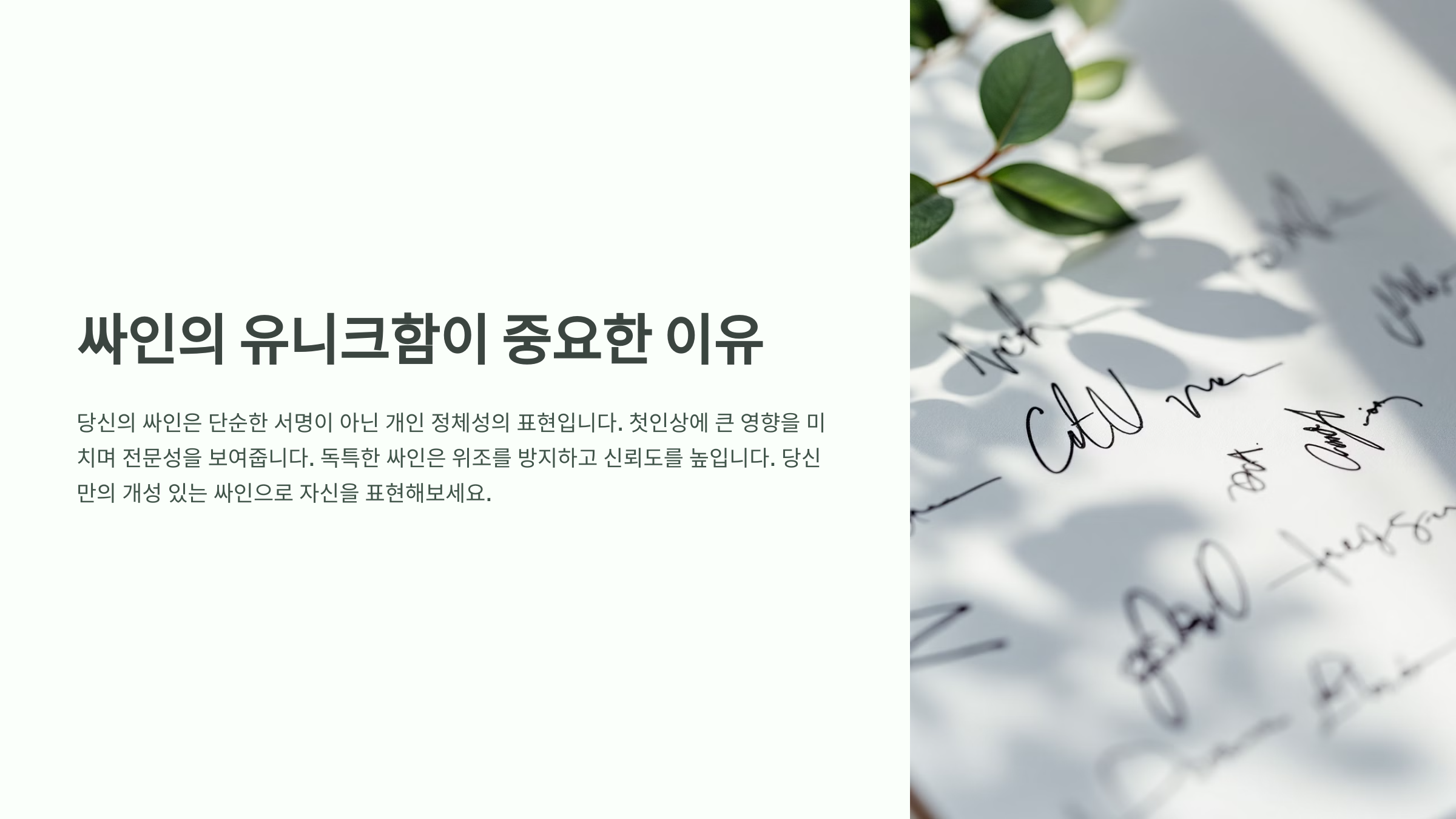
싸인은 단순한 이름이 아니라 개인의 정체성을 나타내는 중요한 요소예요. 특히 공식 문서나 예술 작품, 스포츠 용품 등에 싸인을 남기는 경우, 독창성이 더욱 강조된 답니다.
독창적인 싸인은 위조를 방지하는 역할도 해요. 일반적인 이름만 사 용하는 것보다, 특정한 패턴이나 숫자를 포함하면 모방이 어려워지죠.
싸인의 유니크함이 필요한 분야
분야 이유 연예인 팬들에 게 특별한 의미 부여 스포츠 선수 유니폼 및 용품의 가치 상승 예술가 작품에 독창성 추가 싸인을 특별하게 만들기 위해서는 고유한 요소를 추가하는 것이 중요해요. 그래서 숫자를 활용하는 것이 좋은 방법이 될 수 있죠!
싸인에 숫자를 넣으면 좋은 점
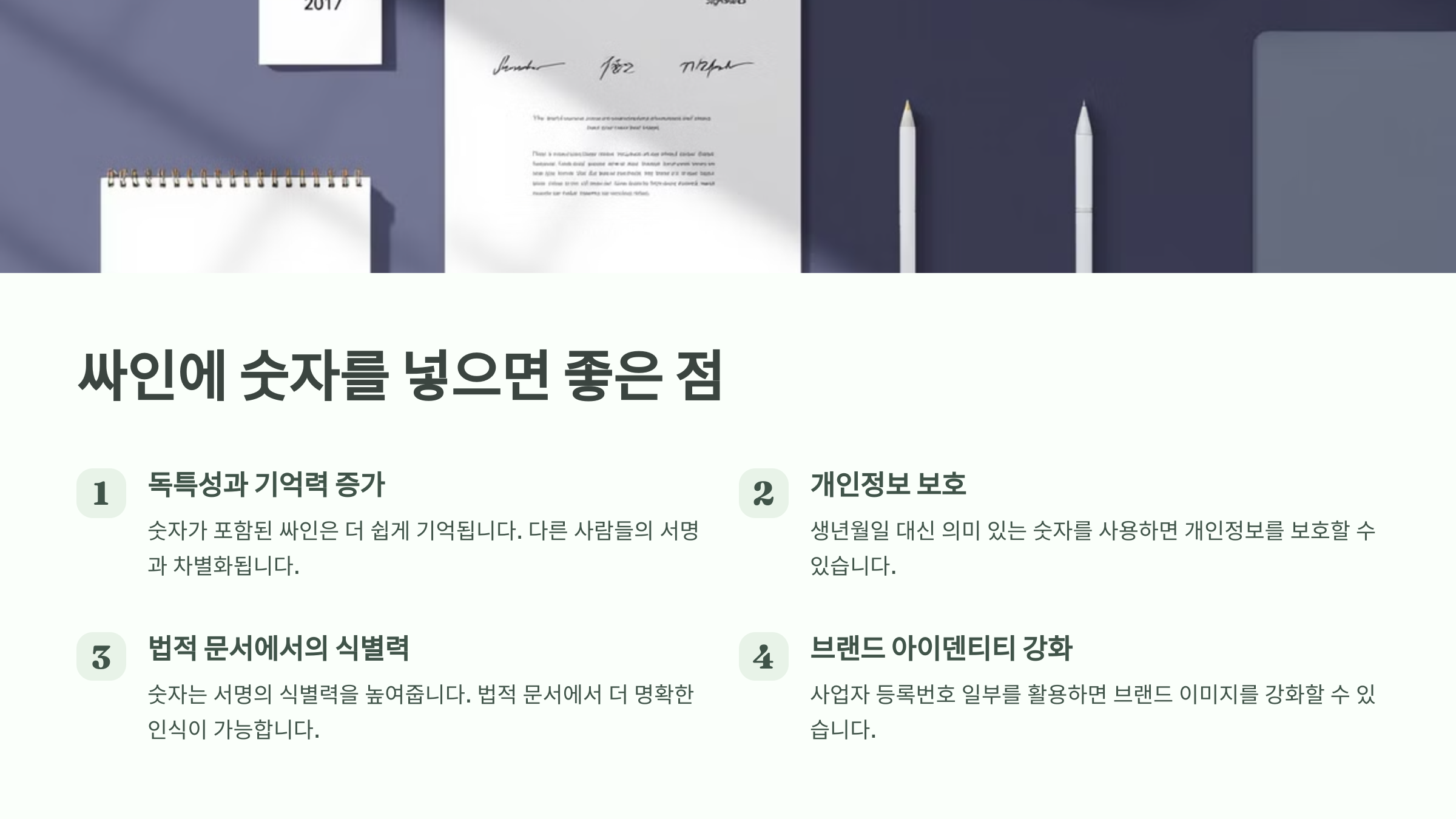
많은 유명인들이 숫자를 싸인에 포함하는 이유는 바로 '차별화' 때문이예요. 평범한 이름보다 숫자가 포함된 싸인은 훨씬 더 개성적이고 기억에 남을 수밖에 없어요.
또한, 숫자는 개인적인 의미를 담을 수 있어요. 예를 들어, 마이클 조던은 23번을 자신의 트레이드마크로 사용했고, 크리스티아누 호날두는 7번을 활용했어요. 이렇게 숫자는 단순한 장식이 아니라 정체성을 강화하는 역할을 해요!
숫자가 포함된 유명한 싸인 예시
유명인 싸인 속 숫자 의미 마이클 조던 23 대표적 인 등번호 싸인에 숫자 넣는 방법 ✍
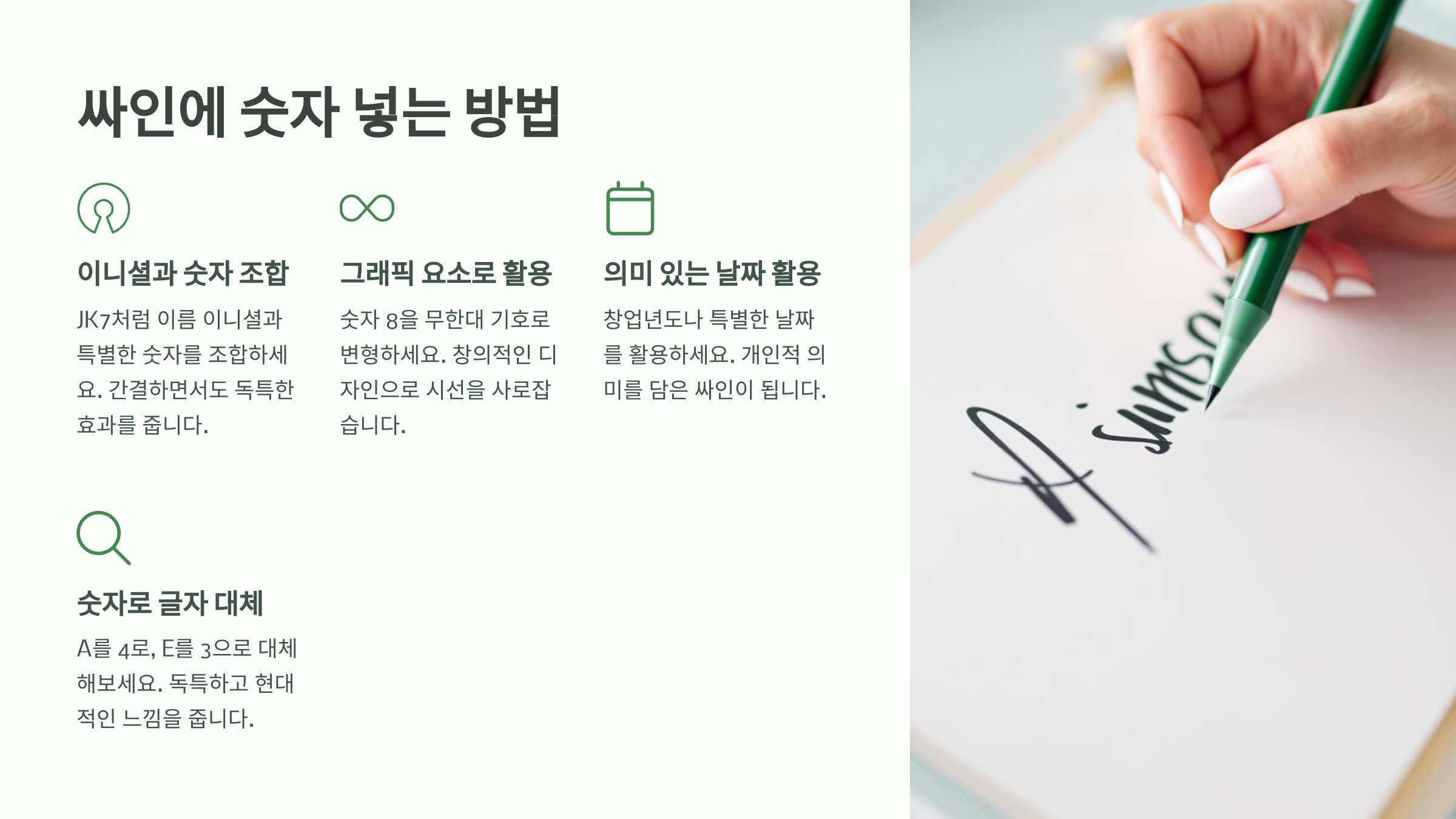
싸인에 숫자를 넣는 방법은 다양해요. 단순히 이름 뒤에 숫자를 붙임 는 것부터, 숫자를 필기체와 결합하여 디자인하는 방식까지 여러 가지 방법이 있죠.
예를 들어, 이름과 숫자를 조합해 ‘KJ23’처럼 만들 수도 있고, 숫자를 도형화해서 싸인 속에 녹여낼 수도 있어요. 이렇게 하면 보다 독창적이고 개성 넘치는 싸인을 만 들 수 있답니다!
숫자를 활용한 싸인 스타일
스타일 설명 이름 + 숫자 예: KJ23, MLee99 숫자 디자인화 숫자를 필기체처럼 변형 기호와 조합 예: ★23, ♡99 이렇게 자신만의 스타일로 숫자를 활용하면 남들과는 다른 유니크한 싸인을 만들 수 있어요. 이제 숫자를 활용해서 더 멋진 싸인을 만들어 볼까요?
숫자를 활용한 유명인의 싸인
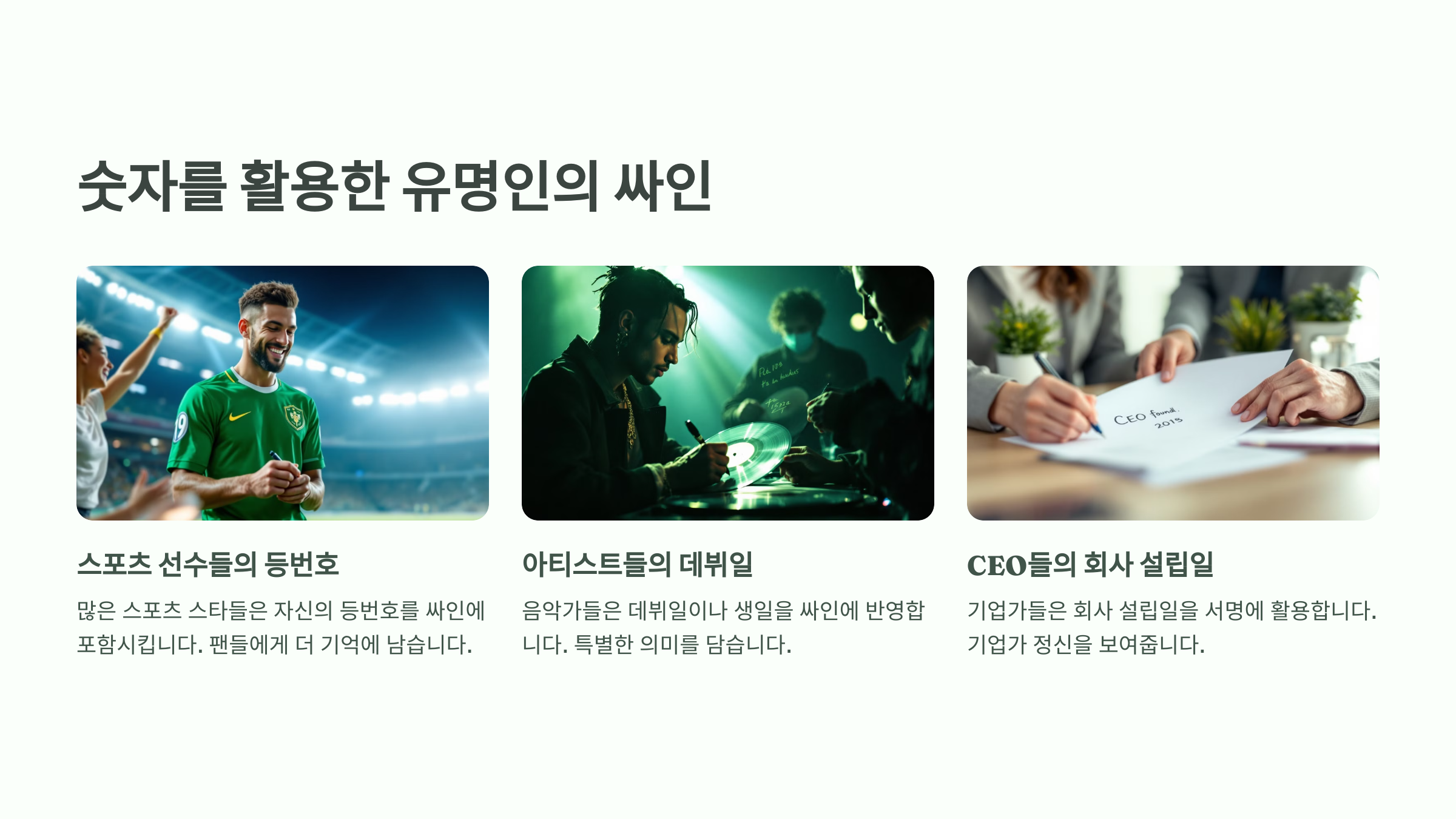
많은 유명인들이 자신만의 상징적인 숫자를 싸인에 포함해요. 이런 숫자들은 보통 등번호, 생년월일, 혹은 특별한 의미를 담고 있죠.
예를 들어, 마이클 조던의 ‘23’, 크리스티아누 호날두의 ‘7’, 코비 브라 이언트의 ‘24’ 등은 모두 그들의 아이덴티티를 나타내는 숫자예요. 싸인에 이 숫자를 넣으면 단 순한 이름보다 훨씬 더 강렬한 인상을 남길 수 있어요!
숫자가 포함된 유명인의 싸인
유명인 싸인 속 숫자 의미 마이클 조던 23 대표적 인 등번호 크리스 티아누 호날두 7 CR7 브랜드 코비 브라이언트 8, 24 두 개 의 상징적인 등번호 데이비 드 베컴 7 맨유 및 잉글랜드 대표팀에서 사용 이처럼 숫자는 단순한 장식이 아니라, 강력한 상징성과 브랜드 가치를 갖고 있어요. 숫자를 활용하면 싸인을 더욱 개성 있게 만들 수 있답니다! ✨
나만의 개성 있는 싸인 만드는 팁 ✍
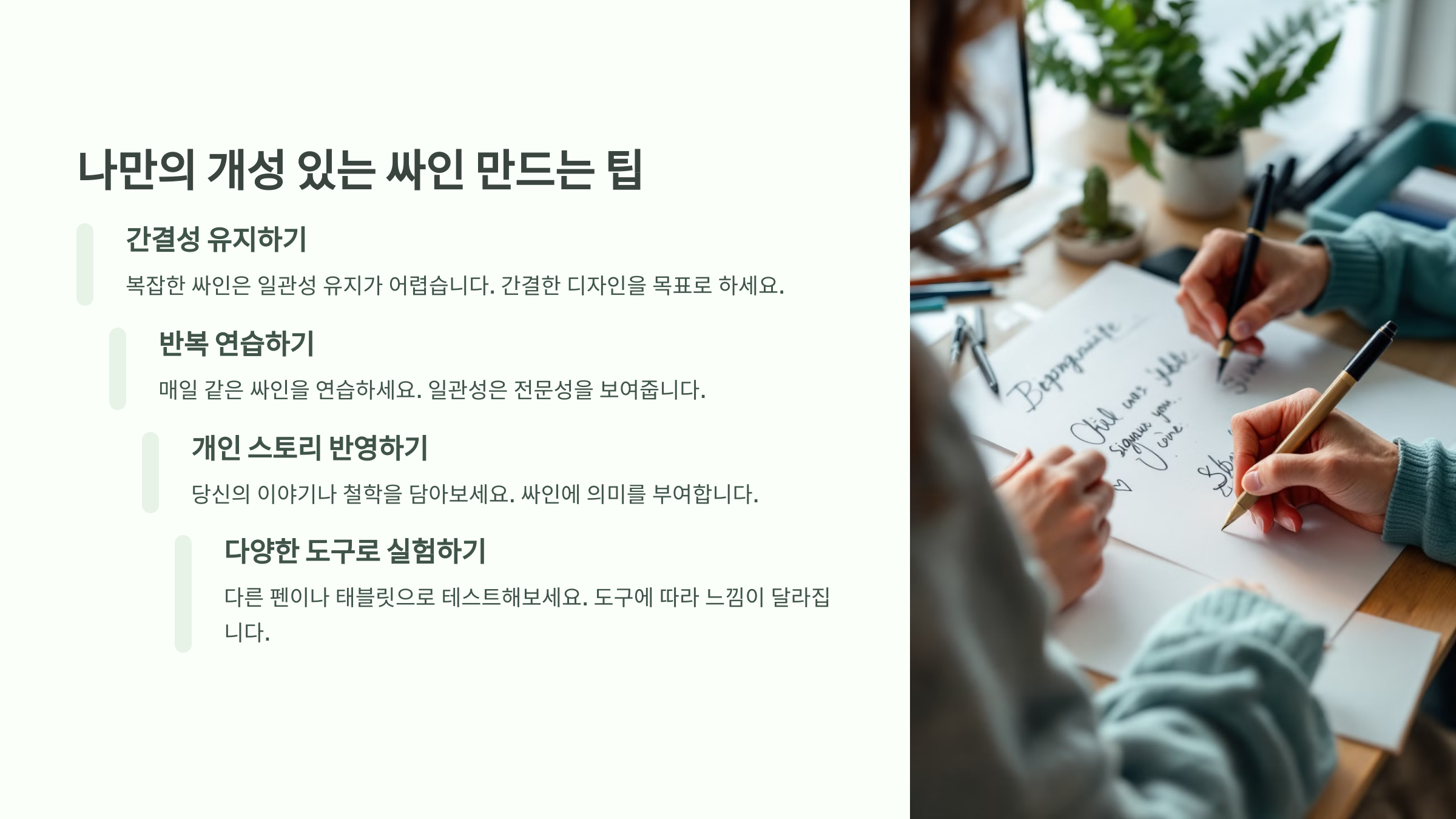
싸인은 단순한 이름을 넘어, 나를 대표하는 하나의 상징이 될 수 있어 요. 그렇다면 어떻게 하면 더 멋지고 개성 있는 싸인을 만들 수 있을까요?
이름의 초성을 활용하거나, 필기체로 변형하는 것도 좋은 방법이에 요. 여기에 숫자나 기호를 추가하면 더욱 독창적인 싸인이 완성된답니다!
개성 있는 싸인을 만드는 방법
방법 설명 초성 활용 예: 김 지훈 → KJH 필기체 변형 영어 또는 한글 필기체 응용 숫자 추가 예: KJH23, MLee99 기호 결합 예: ♡, ★, ∞ 등과 조합 자신만의 스타일을 찾는 것이 중요해요. 여러 번 연습하면서 가장 편 하고 자연스러운 싸인을 찾아보세요! ✨
싸인과 법적 효력 ⚖
싸인은 단순한 장식이 아니라 법적으로 중요한 역할을 해요. 계약서, 신분증, 금융 거래 등 다양한 곳에서 싸인이 본인의 의사를 증명하는 수단으로 사용되죠. ✍
하지만 싸인이 유효하려면 몇 가지 중요한 조건이 필요해요. 단순히 이름을 적는다고 다 법적 효력이 있는 것은 아니기 때문에, 싸인을 만들 때 주의해야 할 점들을 알아볼까요?
⚖ 싸인의 법적 효력을 위한 조건
조건 설명 고유성 다른 사람과 중복되지 않아야 함 일관성 항상 동일한 형태로 작성해야 함 본인의 의사 강요 없이 자발적으로 작성해야 함 위조 방지 위조되 기 어렵도록 디자인해야 함 이러한 조건을 만족하면, 싸인은 법적으로 효력을 가지게 돼요. 따라 서 싸인을 만들 때 신중하게 디자인하는 것이 중요하답니다!
FAQ ❓
Q1. 싸인에 숫자를 넣으면 법적으로 문제가 되나요?
A1. 아니요! 싸인은 본인을 식별할 수 있으면 되기 때문에 숫자를 포 함해도 법적 효력에는 문제가 없어요. 단, 항상 동일한 싸인을 유지하는 것이 중요해요. ✅
Q2. 싸인에 넣을 숫자는 아무거나 사용해도 되나요?
A2. 네, 본인이 의미 있다고 생각하는 숫자를 자유롭게 사용할 수 있어요. 생일, 행운의 숫자, 좋아하는 선수의 등번호 등을 활용하면 좋아요.
Q3. 싸인을 만들 때 주의해야 할 점은?
A3. 싸인은 위조가 어렵고, 항상 동일한 형태로 작성할 수 있어야 해요. 너무 복잡하면 재현하기 어려울 수 있으니 적당한 균형을 맞추는 것이 좋아요. ✍
Q4. 싸인을 변경해도 되나요?
A4. 가능하지만, 중요한 문서에서는 기존 싸인을 유지하는 것이 좋아 요. 싸인을 변경하면 신분 확인 과정에서 문제가 생길 수도 있어요. ⚠
Q5. 싸인을 연습하는 가장 좋은 방법은?
A5. 여러 스타일을 시도해 보고, 가장 자연스럽고 편한 형태를 찾아 반복적으로 연습하는 것이 좋아요. 종이에 여러 번 써보면서 나만의 싸인을 만들어 보세요!
Q6. 싸인을 디지털 서명으로 사용할 수 있나요?
A6. 네! 스캔하거나 태블릿으로 싸인을 만들어 디지털 서명으로 사용할 수 있어요. 일부 공식 문서에서는 전자 서명이 법적으로 인정되기도 해요.
Q7. 싸인을 멋지게 꾸미는 팁이 있을까요?
A7. 필기체 스타일을 연습하거나, 이름의 일부를 기호화하는 것도 좋은 방법이예요. 숫자나 기호를 추가해 나만의 독창적인 싸인을 만들어 보세요!
Q8. 유명인의 싸인을 참고해도 될까요?
A8. 참고는 가능하지만 그대로 따라 하면 안 돼요! 유명인의 싸인을 그대로 사용하면 위조로 오해받을 수 있으니, 자신의 개성을 담아 변형하는 것이 좋아요.